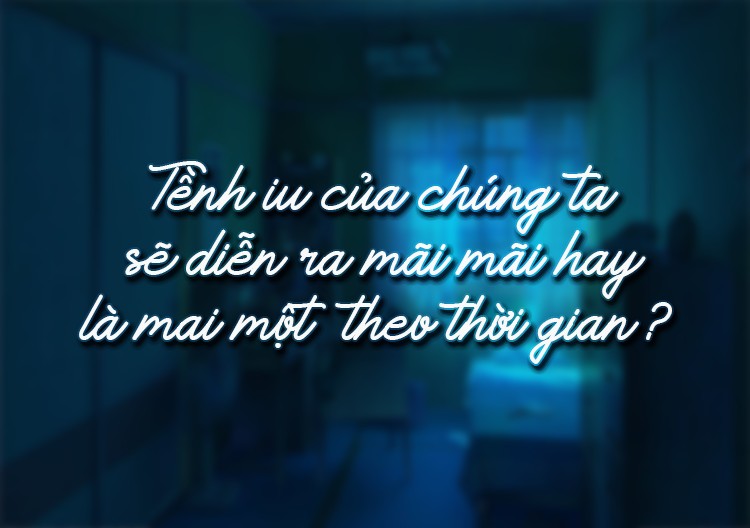
Giới thiệu về Font việt hoá MJ Sunderlines
Trong thế giới đồ họa hiện đại, việc lựa chọn Font Chữ phù hợp đóng vai trò quan trọng để truyền tải thông điệp hiệu quả. Font việt hoá MJ Sunderlines là một bộ phông chữ độc đáo, mang phong cách vẽ tay đầy phóng khoáng và nghệ thuật. Với các đường nét thanh mảnh kết hợp cùng những nét gạch chân đặc trưng, bộ font này tạo nên một dấu ấn thị giác mạnh mẽ, giúp tác phẩm của bạn trở nên sinh động và gần gũi hơn bao giờ hết.
Đặc điểm nổi bật của bộ font
Được thiết kế tỉ mỉ, Font việt hoá MJ Sunderlines hỗ trợ đầy đủ bộ gõ tiếng Việt, giúp người dùng dễ dàng ứng dụng vào các phần mềm như Photoshop, Canva hay Word mà không lo lỗi hiển thị. Những đường nét uốn lượn tự nhiên của MJ Sunderlines rất phù hợp cho các bạn học sinh, sinh viên thực hiện báo tường, thiệp chúc mừng hoặc các dự án trang trí trường học.
Ứng dụng thực tế của Font việt hoá MJ Sunderlines
Sáng tạo nội dung giáo dục
Sử dụng Font việt hoá MJ Sunderlines trong các bài thuyết trình hay tài liệu học tập giúp bài giảng trở nên bớt khô khan. Giáo viên có thể dùng font này để nhấn mạnh các tiêu đề quan trọng, tạo sự hứng thú cho học sinh trong quá trình tiếp nhận kiến thức mới.
Thiết kế banner và poster
Với phong cách trẻ trung, bộ font này cực kỳ lý tưởng cho các loại banner sự kiện, poster câu lạc bộ hoặc ảnh bìa mạng xã hội. Sự linh hoạt trong đường nét giúp thiết kế của bạn vừa chuyên nghiệp lại vừa mang đậm cá tính riêng biệt.